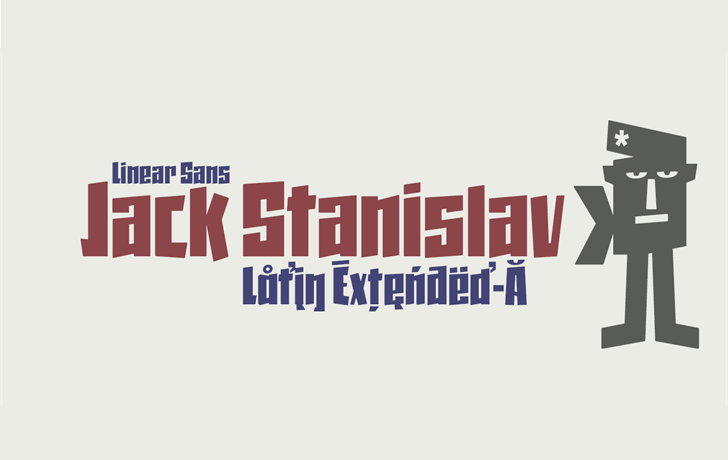
A fonte Jack Stanislav é perfeita para os projetos que exigem criatividade com economia de espaço, seja para headlines ou publicidade onde a originalidade se mescla com eficiência. Seu design retro condensado oferece linhas grossas e um visual divertido, ideal para quem busca um estilo inovador enquanto minimiza o uso da área de impressão. Além disso, seu formato inclinado superior permite criar uma combinação única entre formas horizontais e desafiadoras. As letras curvas descrescentes também contribuem para este movimento, tornando-a ideal para expressar diferentes estilos que adaptam-se facilmente à dinâmica do design no contexto específico de cada projeto. Ideal para aqueles buscando imprimir uma versão fluida de seus projetos gráficos, Jack Stanislav oferece a possibilidade de criar visualizações originais e interessantes, sempre respeitando o formato retro da fonte.